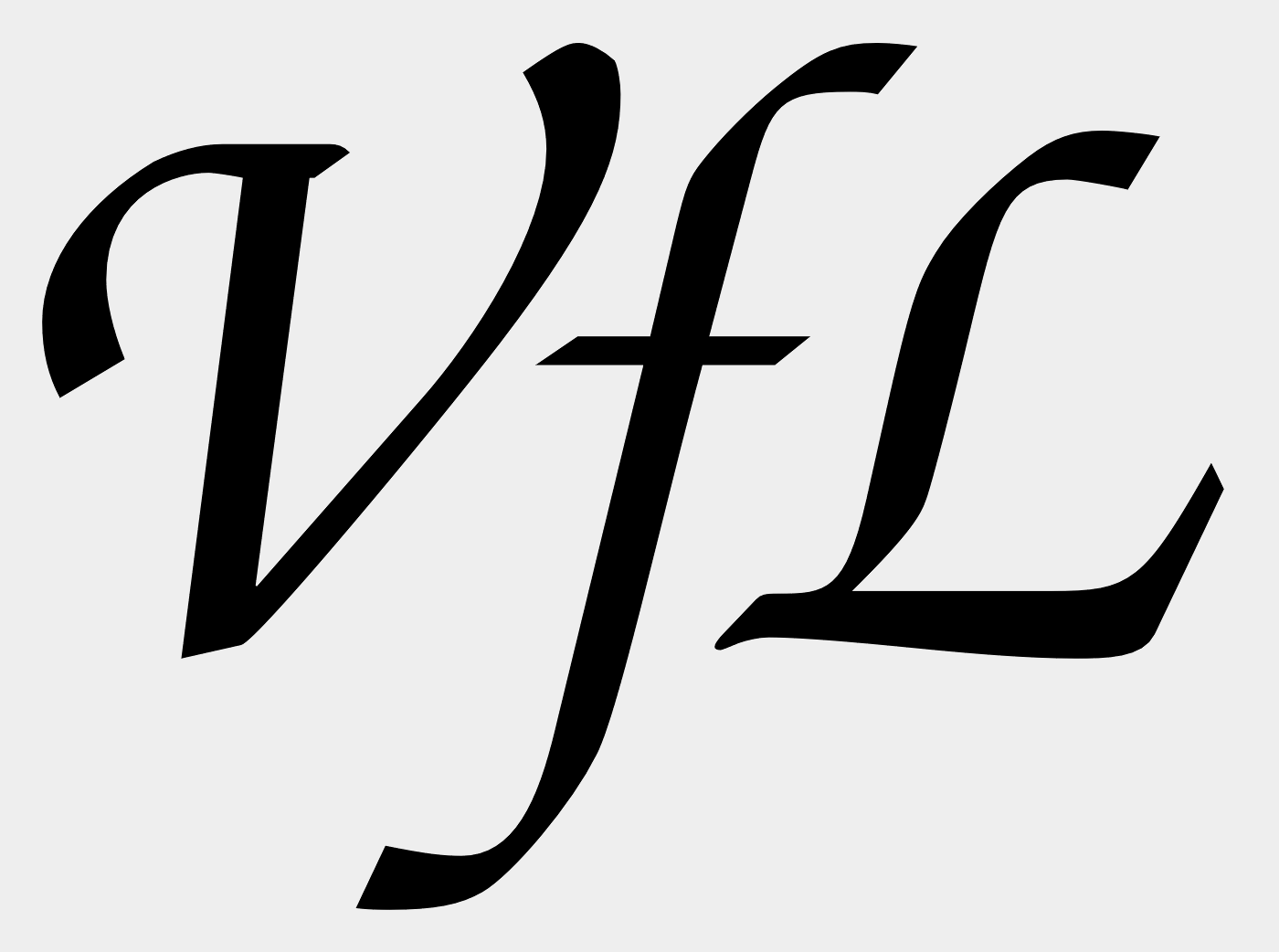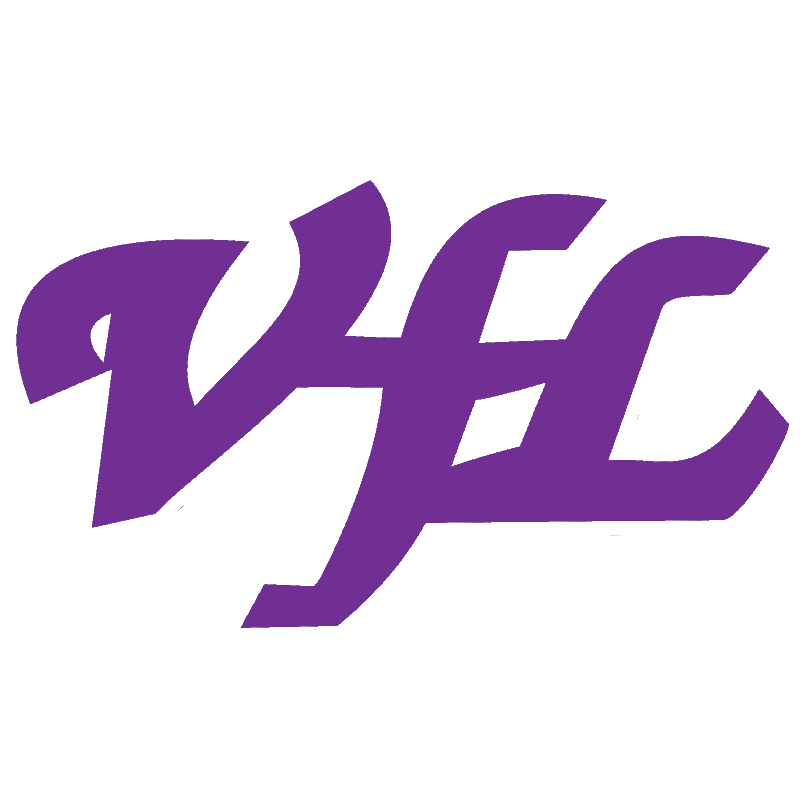
schriftart gesucht (VfL)
ich bin auf der suche nach dieser (oder einer ähnlichen) schriftart.
sie entstammt dem sächsischen sportverein VfL Pirna-Copitz.
sie hat noch einen weissen rand, den man hier eventuell nicht erkennen kann.
Von der Herkunft des Logos, und der Zeit, in der sicherlich das Ur-Logo entworfen wurde, gehe ich von einem handgemachten Entwurf aus, der dann irgendwann ziemlich schlecht digitalisiert wurde.